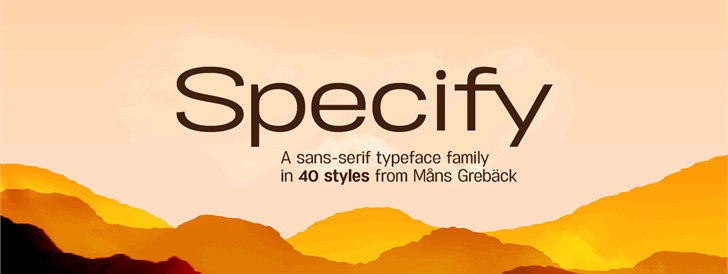
Specify Font Family – Fonte Grátis
Specify Font Family
A fonte ‘Specify Font Family’ é um belo exemplar do tipo sans serif criado pelo designer sueco Måns Grebäck. Com linhas finas e elegantes, esta fonte oferece uma abordagem minimalista que combina perfeitamente com designs modernos e clean. Ideal para uso pessoal, a ‘Specify Font Family’ é um recurso essencial para qualquer designer ou profissional de design gráfico em busca de uma alternativa suave ao tipo tradicional. Para quem deseja incorporá-la em projetos comerciais, Måns Grebäck disponibiliza licenças comerciais no site oficial. Se você tiver dúvidas sobre o uso da fonte ou estiver interessado em propostas de design personalizadas, fique à vontade para entrar em contato pelo email . Visite também o website do designer e acompanhe seu trabalho no Facebook: http://www.facebook.com/aringtypeface.